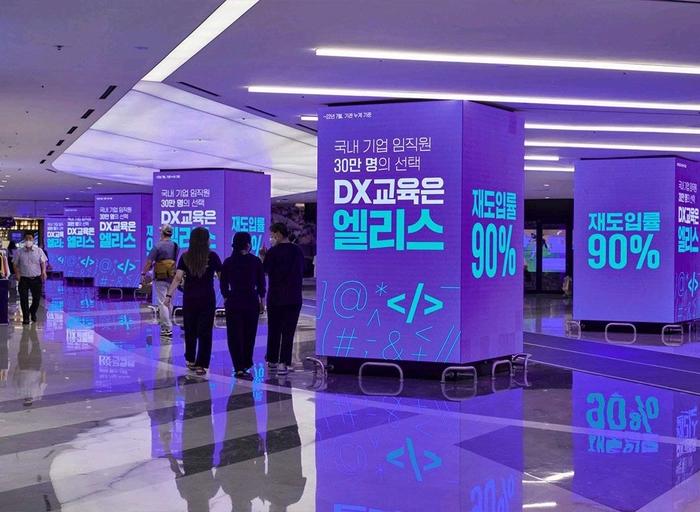
엘리스 DX널리체 무료폰트
엘리스 DX널리체 — 엘리스에서 배포하는 무료 폰트입니다. 깔끔한간결한 네모꼴 구조와 균형 잡힌 획으로 명확한 인상을 주는 현대적인 고딕체 인상의 UI 추천 폰트
엘리스가 2023년 8월에 내놓은 서체로, 세 벌 가운데 가장 범용입니다.
이름을 회사가 직접 풀어 놓았습니다. 디지털 대전환 시대를 주도하며 DX의 가치를 보다 널리 알리고자 하며, 간결하게 디자인하여 활용성이 높은 이 서체로 더욱 많은 사람에게 그 가치가 공유되길 바란다는 것입니다. DX는 디지털 전환을 뜻하고, 널리는 널리 알리고자 한다는 그 문장에서 그대로 왔습니다.
회사가 밝힌 조형은 간결하게 디자인하여 활용성이 높다는 표현이 전부입니다. 개성을 앞세우지 않고 어디에나 무난히 얹히는 쪽을 택했다는 뜻이고, 실제로 브랜드 서체치고 특징이 옅다는 평도 있습니다. 그것이 단점이자 장점입니다.
굵기는 Light와 Regular, Bold 세 가지로 세 벌 중 가장 많아 본문과 제목, UI를 한 벌로 처리할 수 있습니다. 반대로 브랜드를 각인시켜야 하는 헤드라인에는 밋밋합니다. 오픈 폰트 라이선스로 배포되어 수정과 재배포가 자유롭습니다.